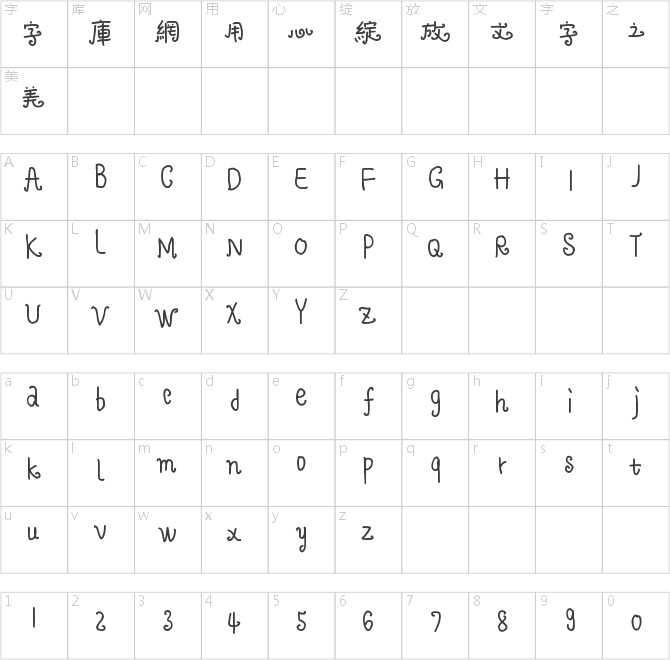
字體名稱: 造字工房丁丁手
造字工房丁丁手繪
造字工房丁丁手繪字體字庫(kù)是一款讓人賞心悅目、百看不厭的中文字體,適合各類廣告和產(chǎn)品包裝設(shè)計(jì)應(yīng)用,字體大小5.55MB,格式為ttf字體,上傳用戶是改一個(gè)名字呀,作者/版權(quán)方為造字工房